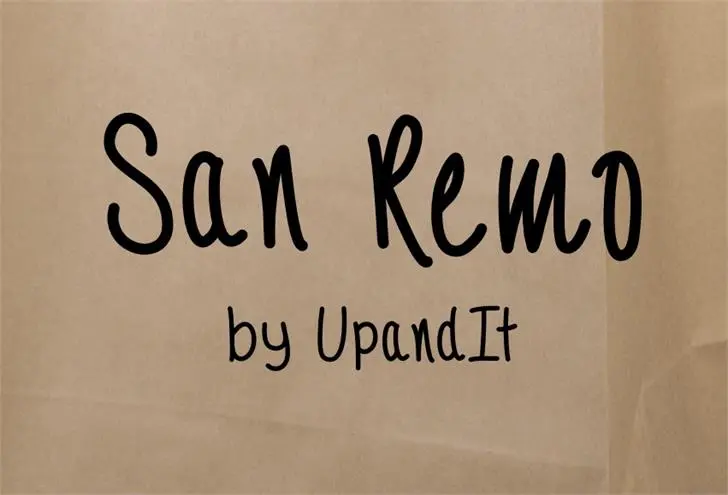
A SanRemo Font é uma mão-dura que transmite uma sensação aconchegante e natural perfeita para criações criativas. Seja você um designer ou um amante de design, a SanRemo pode ser sua próxima paixão, oferecendo linhas suaves e detalhes finos que garantirão seu diferencial na produção visual. Feito pelo talentoso Hamilton, o estilo da fonte transmite uma verdadeira experiência de escrever com suas próprias mãos, resultando em letras cuidadosamente redondas que parecem ser escritas a mão. Se você está planejando utilizar essa fonte para projetos comerciais, Hamilton está à disposição para conversar sobre como explorar ainda mais o potencial desta fonte única e versátil. A SanRemo é uma escolha inteligente se você deseja dar um toque personalizado a qualquer projeto visual.